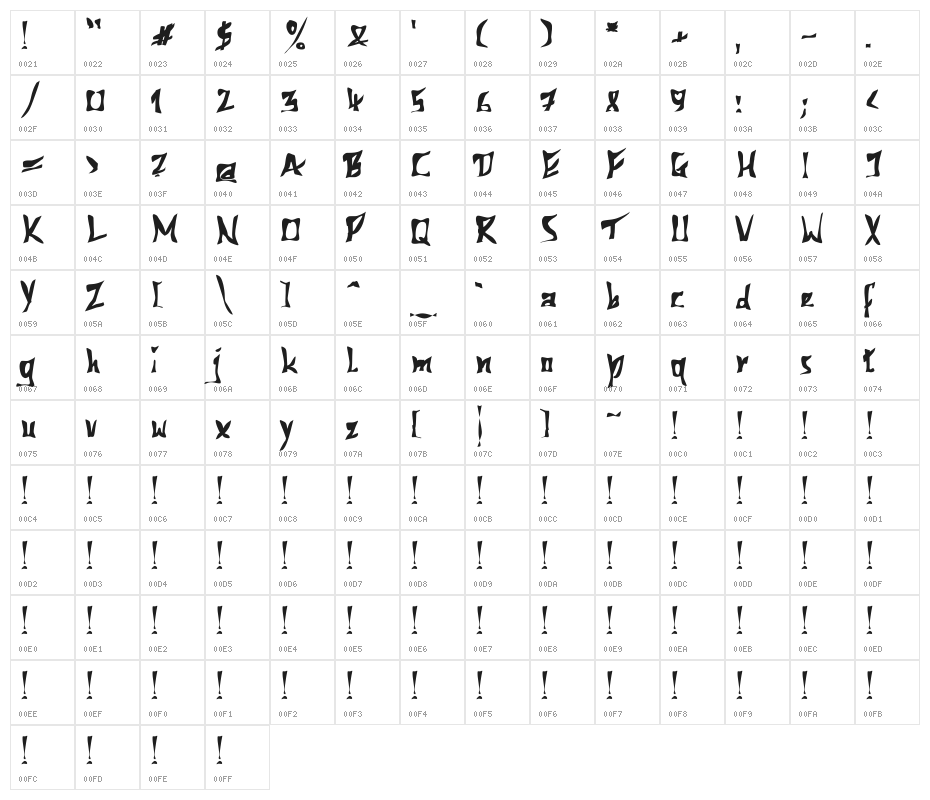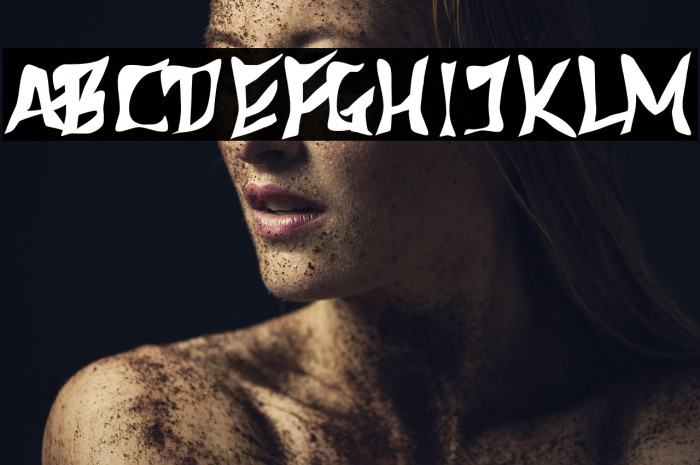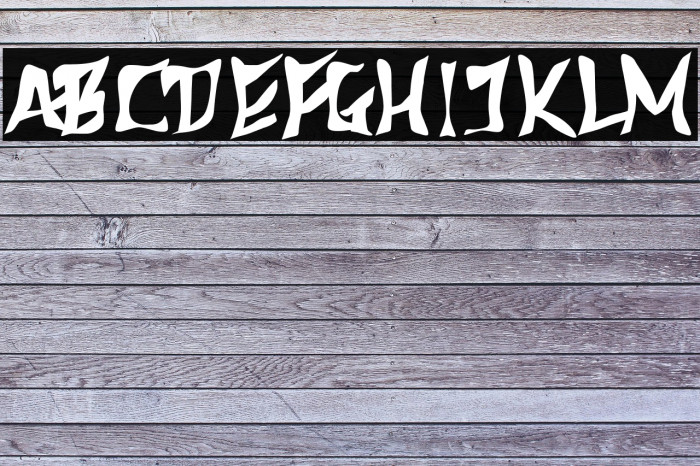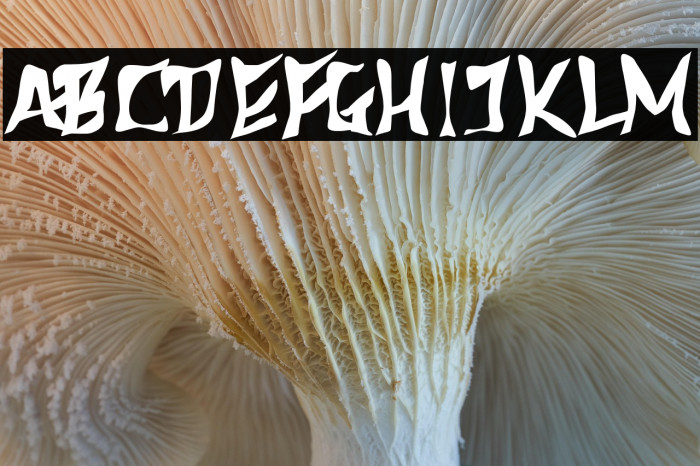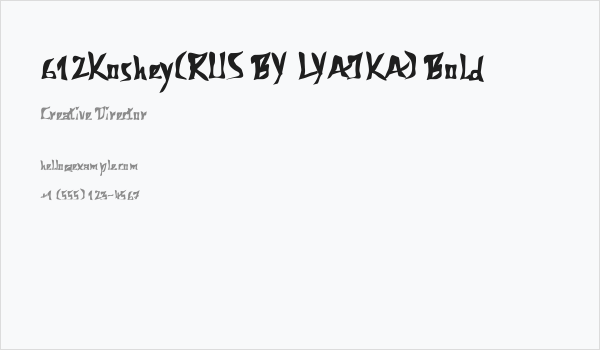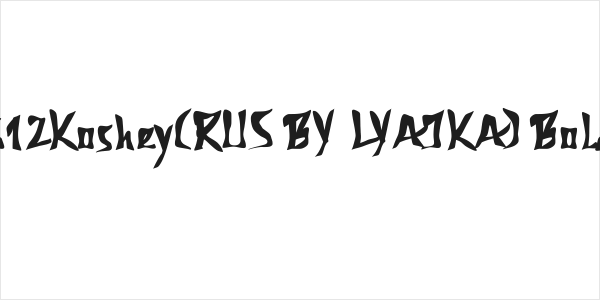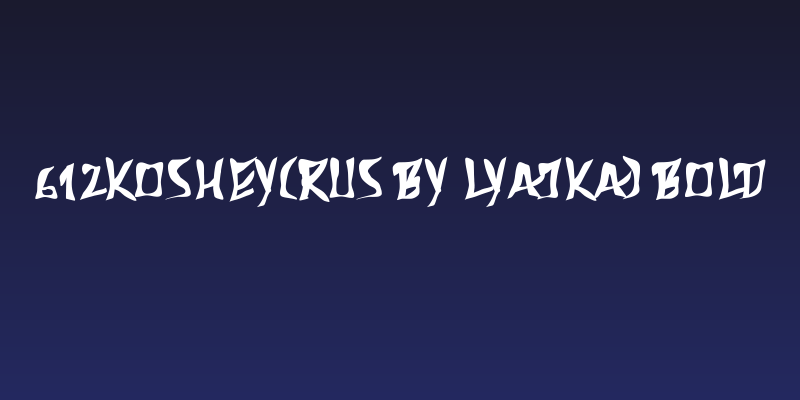
612Koshey(RUS BY LYAJKA) Bold Font
| 名称 | 612Koshey(RUS BY LYAJKA) Bold |
| 分类 | Graffiti |
| 推荐项目 | Ideal for projects requiring a bold, artistic touch such as posters, album covers, or branding for creative industries. |